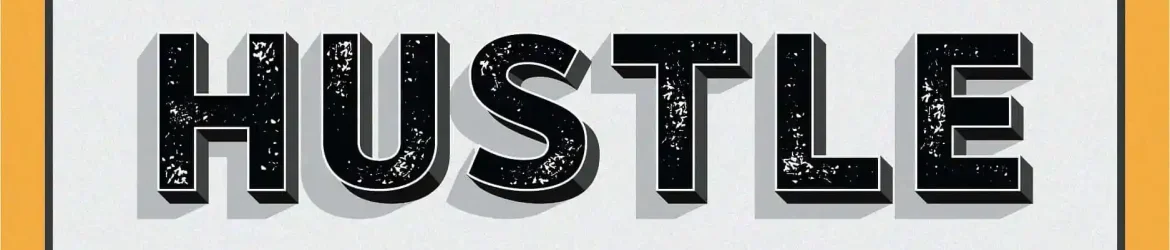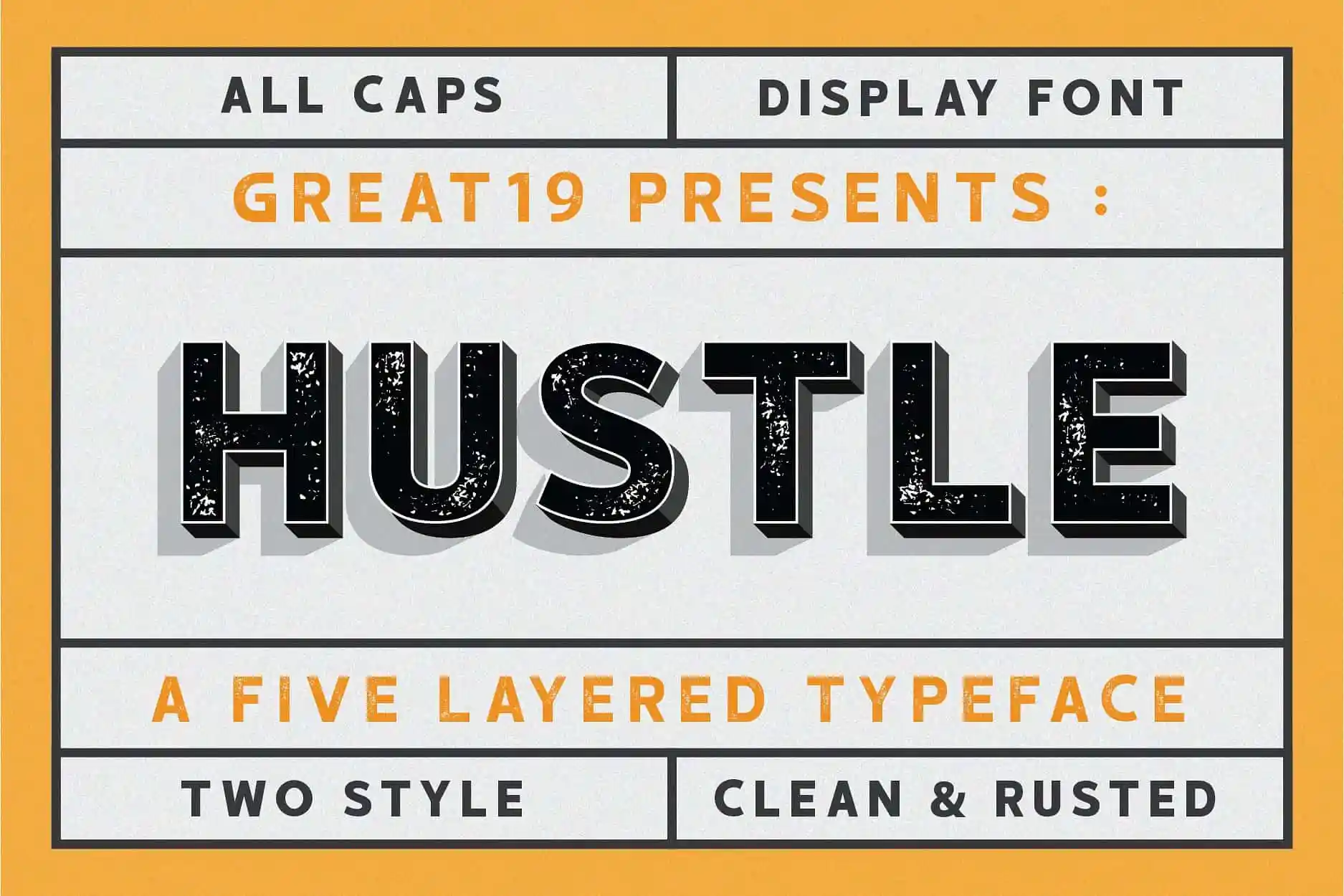
Hustle Display Font – Fonte Grátis
Hustle Display Font
Descubra a Hustle Display Font, uma elegante família de tipos de exibição com cinco camadas que oferece inúmeras possibilidades para designers de arte digital e gráficos. Lançada pelo designer 1001fonts, esta fonte é perfeita para títulos, headlines, logotipos, selos, emblemas, panfletos, sinais, exibições, rótulos e embalagens de alta qualidade. A Hustle Display Font é uma criação que combina um toque vintage industrial com o ar moderno do clean top layer. Com duas opções de estilo (clean & rustic), ela oferece muitas variações para texturas interessantes e design único, criando ambientes de marca ou produto repletos de energia e personalidade. Suave mas forte ao mesmo tempo, a Hustle Display Font é perfeita para ilustrar qualquer tipo de arte digital. Combinada com sua arquitetura meticulosa em cinco camadas, esta fonte não apenas se destaca por seus detalhes cuidadosamente pensados, mas também oferece uma versatilidade que permite criar um design único e impecável. Não perca tempo; é hora de explorar a exibição vibrante da Hustle Display Font para seu próximo projeto visual!